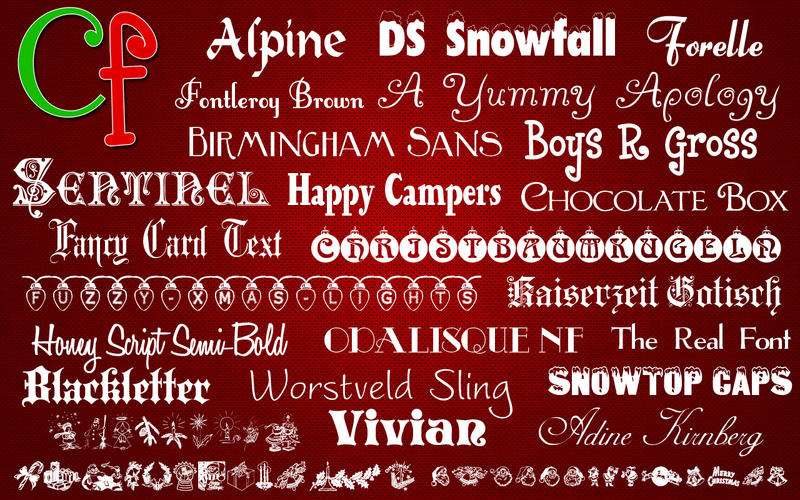
Christmas Collection è una raccolta gratuita di 40 font a tema natalizio creati da designer professionisti in vari stili, ottimi per le prossime festività. Grazie a questo pacchetto possiamo aggiungere al nostro Mac caratteri perfetti per creare calendari, biglietti di auguri, sfondi scrivania, brochure, inviti a feste, siti web e molto altro ancora.